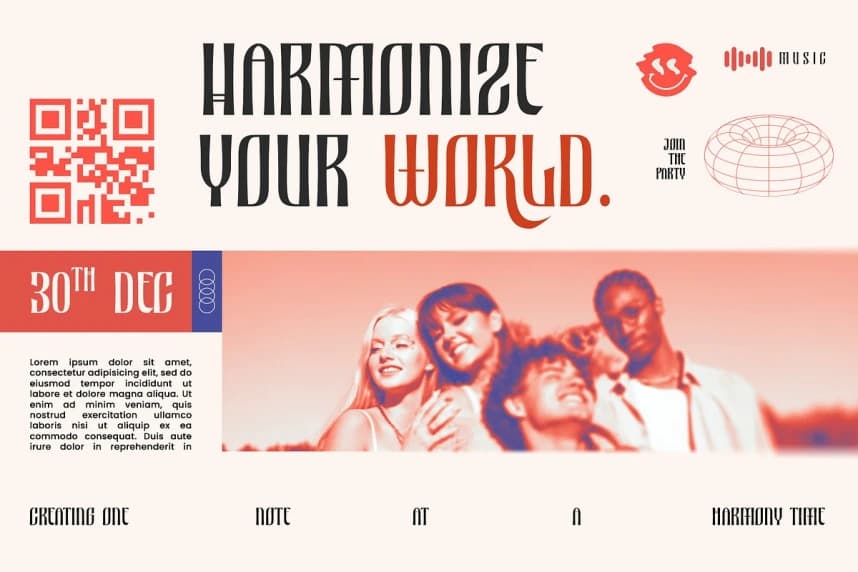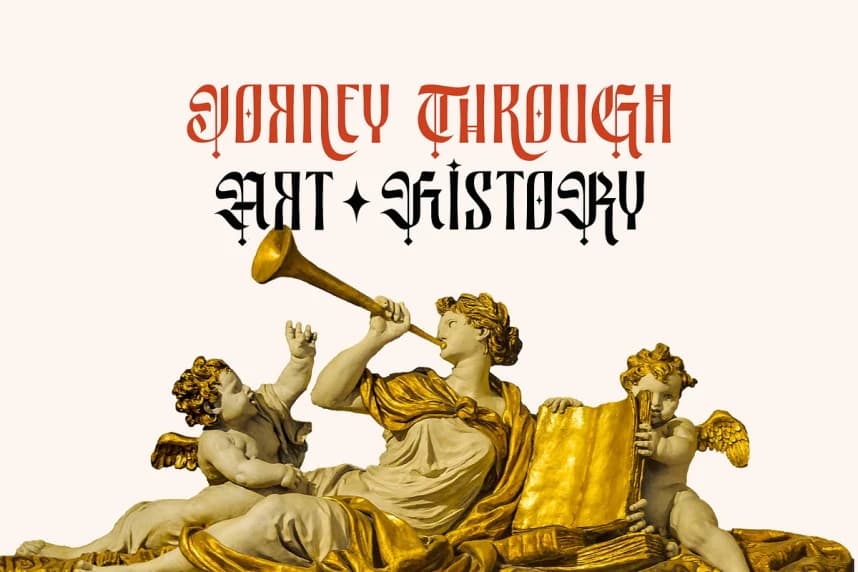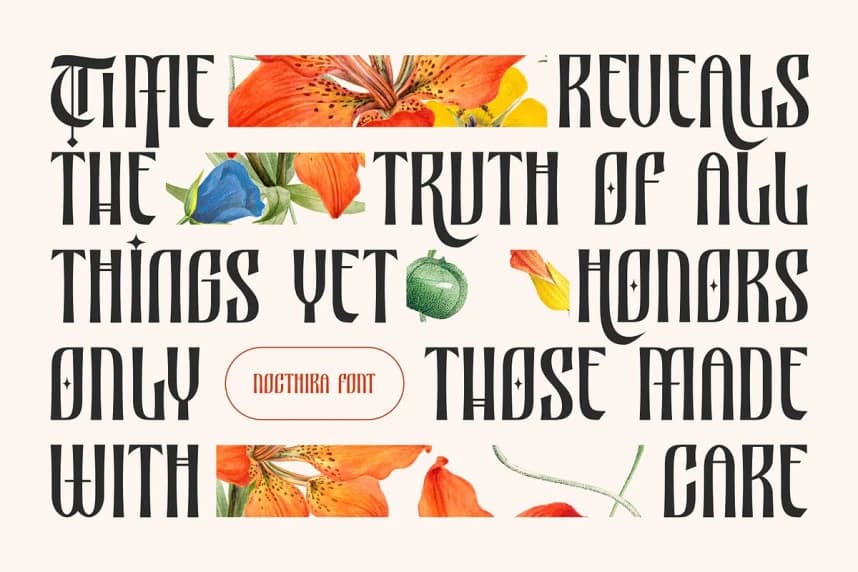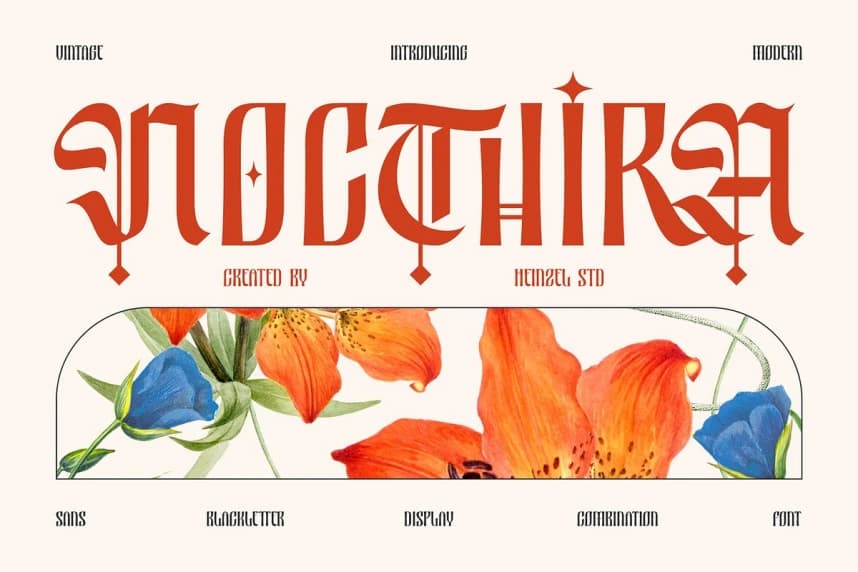
Nocthira Font, vintage gotik zarafeti ile rafine bir modern dokunuşu birleştiren cesur ve sanatsal bir blackletter yazı tipidir. Klasik Orta Çağ yazı stilinden ilham alan Nocthira, dramatik hatlar, keskin serifler ve süslü detaylar barındırır ve güçlü bir etki yaratır.
Nocthira Font, vintage gotik zarafeti ile rafine bir modern dokunuşu birleştiren cesur ve sanatsal bir blackletter tipografisidir. Klasik Orta Çağ yazı tiplerinden ilham alan Nocthira, dramatik hatlar, keskin serifler ve süsleyici detaylar sunar ve bu da güçlü bir etki yaratır